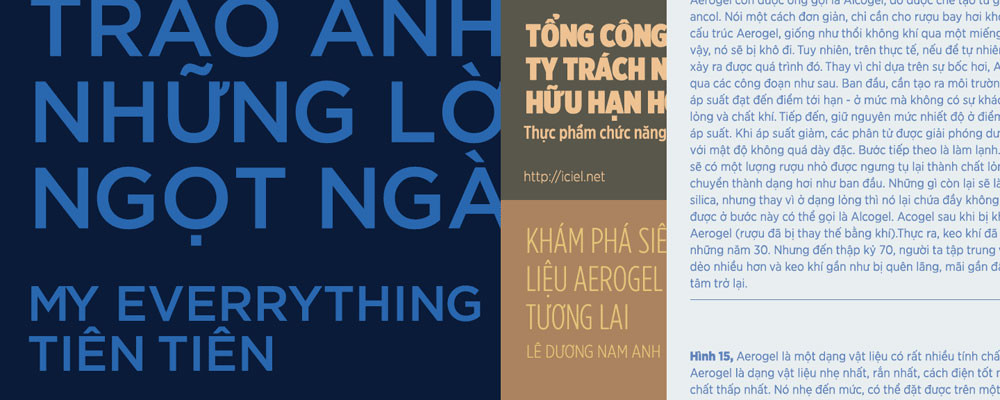
Фирменный стиль — это комплекс корпоративной атрибутики, которая индивидуализирует компанию среди прочих. Фирменный стиль в широком понимании — это использование единых принципов оформления, цветовых сочетаний и образов для всех форм рекламы деловых бумаг, технической и других видов документации, офиса, упаковки продукции.
Существуют четыре возможных цветовых решения Логотипа.
Основная цветовая комбинация:
Товарный знак и надпись имеют цвет #334453.
Цвет чистый, среднего тона.
Сочетается с цветовыми традициями компании ГАРАНГРЕСУРС.Основной фон — жёлтый с использованием охранного поля.Шрифт Gotham Pro Regular, используется как фирменный.
Gotham Pro Regular использования в буклетах и листовках;
Дизайн Gotham Font
Ключевым моментом является то, что цели, для которых они предназначены, служат вашими макетами. Вы будете поражены тем, как может выглядеть дизайн с 3D-шрифтами, просто выбрав потрясающий шрифт Gotham без засечек. Бумага на руке имеет текст, созданный множеством точек, образующих разрешение.